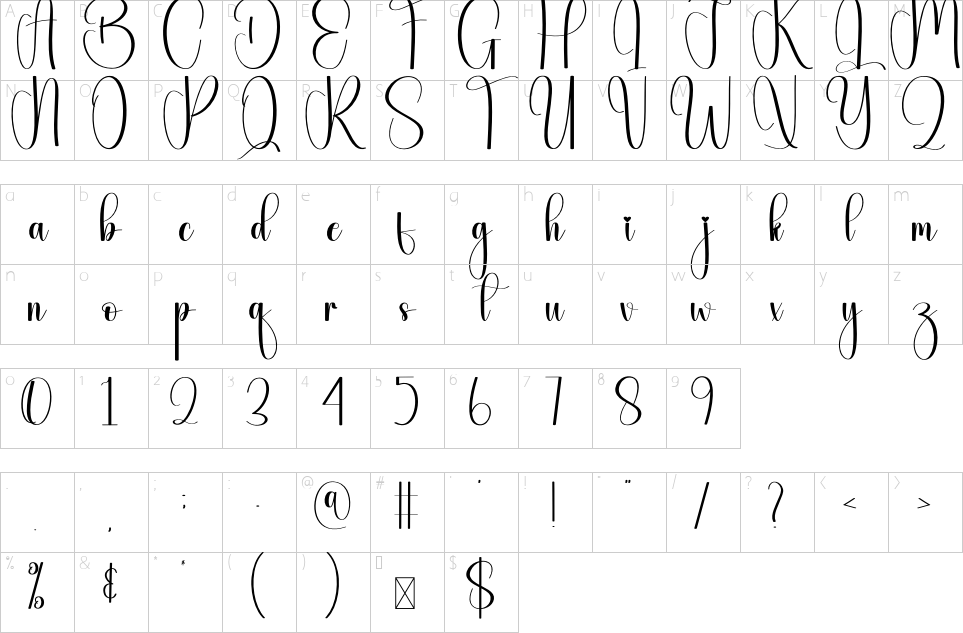
Autography Font – Download Grátis
Descubra a elegância da Autography font, perfeita para designers gráficos apaixonados. Desenvolvida por William Jhordy, esta fonte foi projetada com uma paixão pelo design e pela estética moderna. Com seu design clean e fácil de ler, a Autography font oferece uma opção versátil para seus projetos digitais. Não importa se você está trabalhando em um layout de revista, criação de materiais de marketing ou desenvolvimento de sites, esta fonte garante um estilo único e profissional. Com seu design limpo e moderno, a Autography font é uma escolha inteligente para quem procura uma fonte de alta qualidade que não custa muito. Baixe agora e descubra por si mesmo porque a Autography font é uma escolha de download certa.